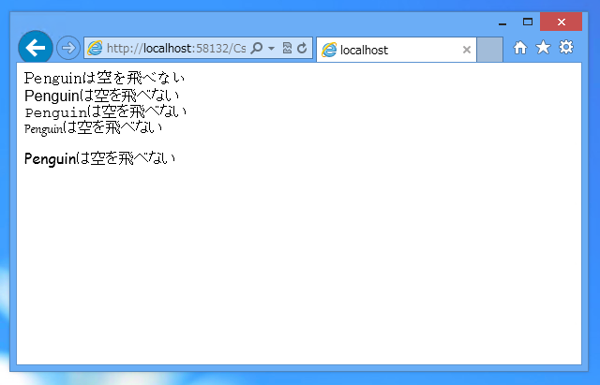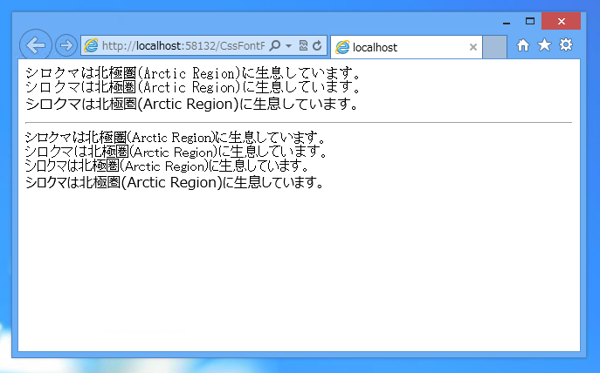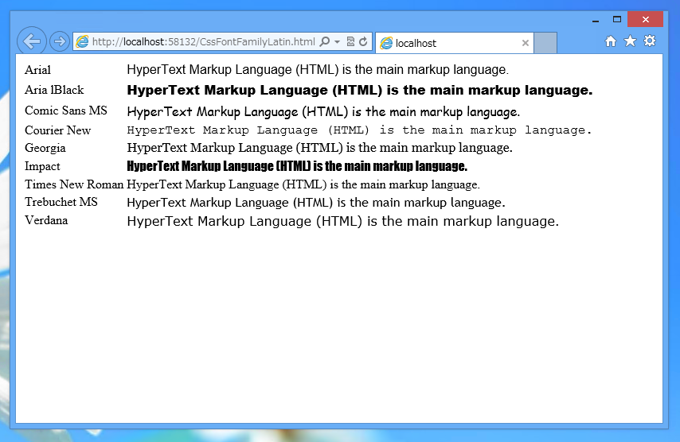
スタイルシートで文字のフォントを変更するコードを紹介します。
フォントを変更する場合はfont-familyプロパティを設定します。
フォントファミリーを示すキーワードでフォントファミリーを指定できます。キーワードは以下があります。
| キーワード | 説明 |
|---|---|
| sans-serif | ゴシックスタイルのフォントファミリーです |
| serif | ひげのついた書体や明朝スタイルのフォントファミリーです |
| cursive | 筆記体や草書体などの手書きスタイルのフォントファミリーです |
| fantasy | 草食系のフォントファミリーです |
| monospace | 等幅フォントファミリーです |
上記のHTMLファイルを表示すると下図の結果となります。
フォントの書体が変更されていることが確認できます。
フォント名を指定する場合はフォント名を「"」または「'」で囲んで指定します。
上記のHTMLファイルを表示すると下図の画面が表示されます。スタイルシートに設定したフォントで文字が描画されています。
Window,Macで共通に利用できる欧文フォントは以下があります。
下記コードを記述します。
上記のHTMLファイルを表示すると下図の結果となります。